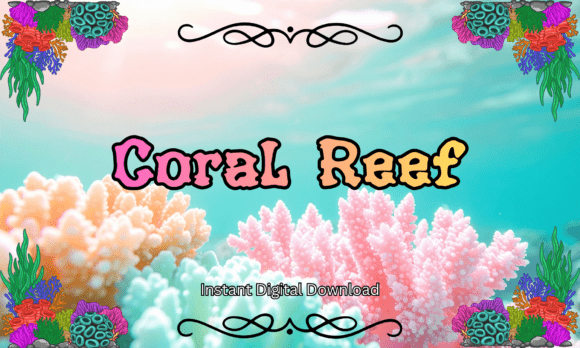
Coral Reef
إذا كنت تبحث عن أصول عالية الجودة مثل Coral Reef، فإن هذه الحزمة المميزة هي خيار رائع لمشاريعك الإبداعية.
تم تصميمه بدقة، ويوفر Coral Reef متجهات نظيفة وطباعة سلسة وترخيصًا تجاريًا لراحة بالك.
سواء كنت تقوم بإنشاء منتجات الطباعة عند الطلب أو دعوات الزفاف أو رسومات وسائل التواصل الاجتماعي، فإن Coral Reef هو الخيار المثالي.